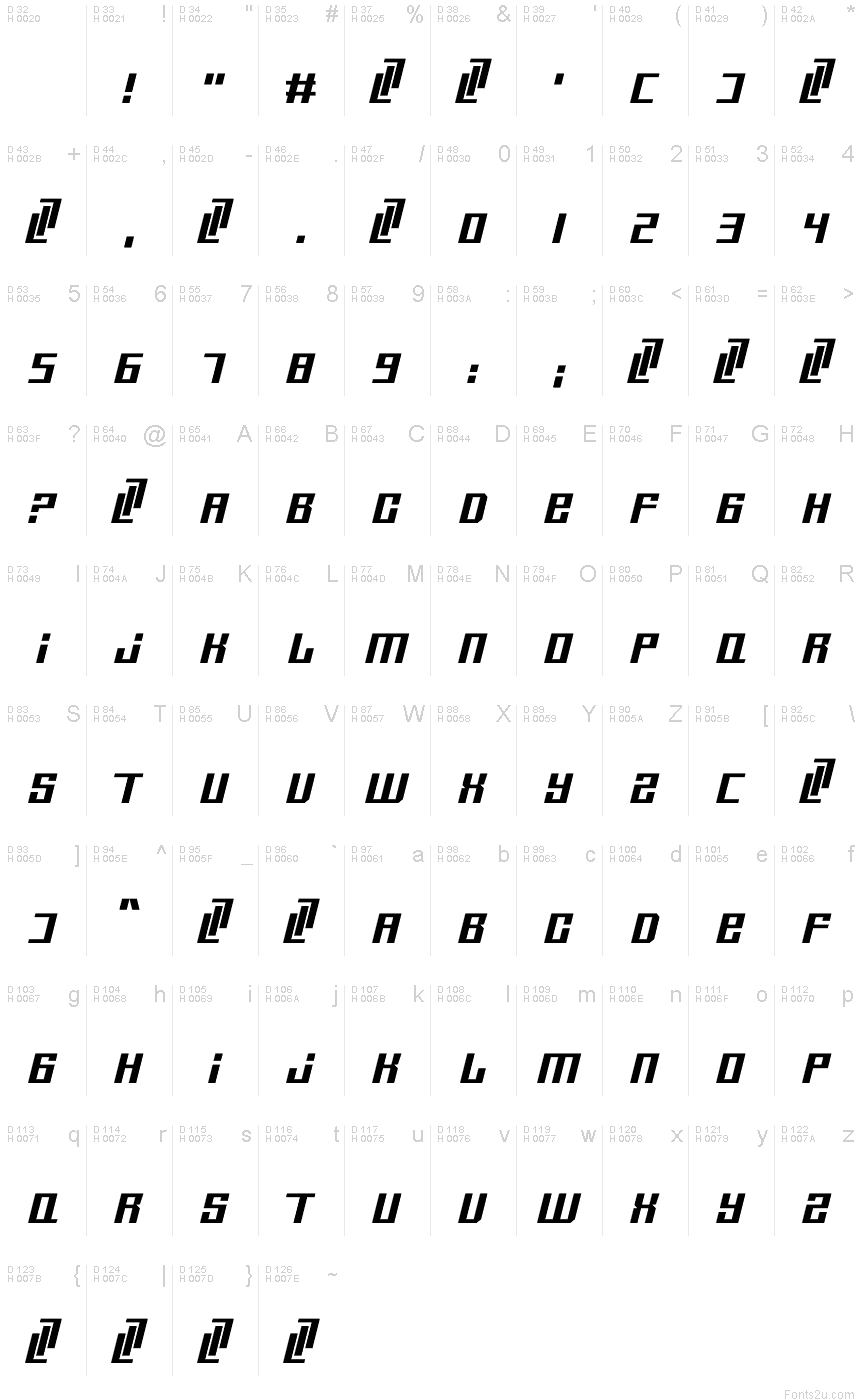
Tristar New, bezplatné techno display písmo navržené studiem Treestaar pro Laplakett, sází na rychlý herní styl s robustními písmeny a ostrými diagonálními řezy. Písmo působí kompaktně a mechanicky, ale ne chladně – díky opakujícím se zářezům a hranatým tvarům připomíná motion graphics, arkádovou estetiku a raný digitální hardware.
Skvěle funguje na plakátech, titulcích, esportové grafice, kartičkách s názvy, klubových letácích a krátkých logotypech, kde pár písmen stačí k vyjádření postoje. Jako font zdarma se Tristar New nejlépe hodí pro krátké displejové aplikace, zejména pokud hledáte úderný, futuristický rytmus bez sklouznutí k laciným sci-fi klišé.